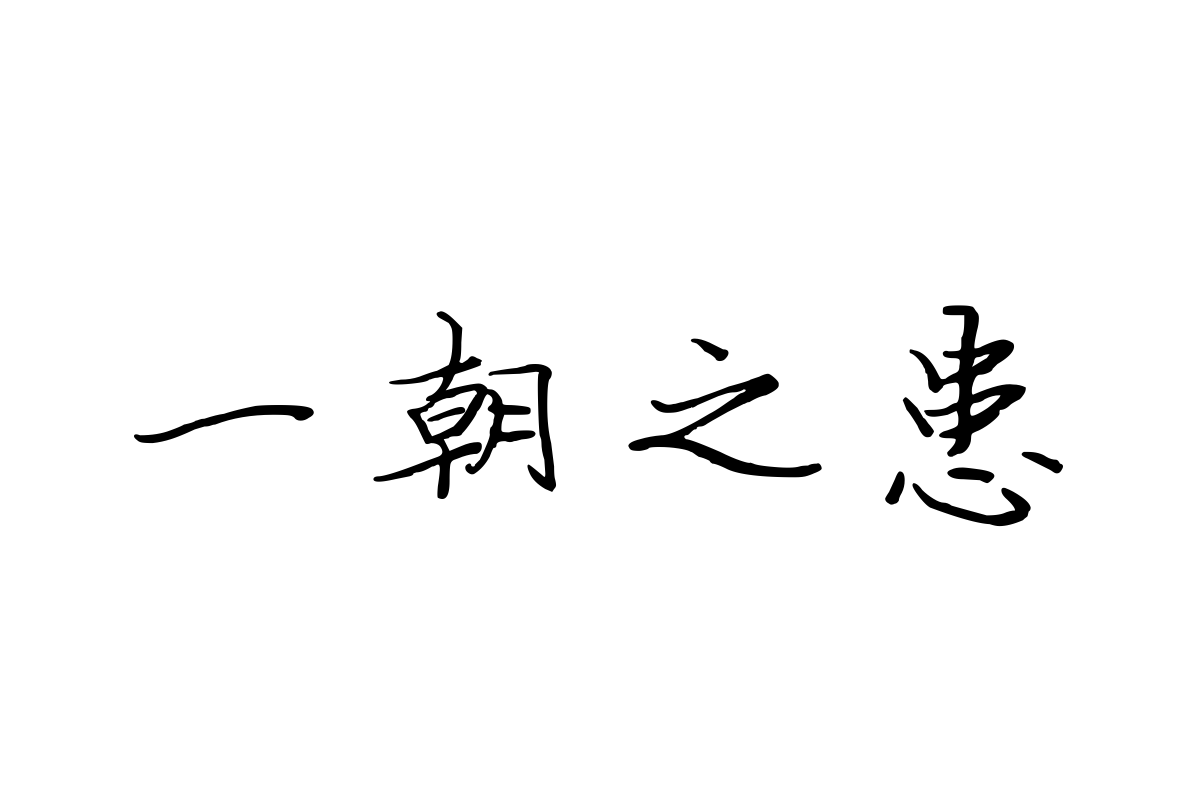
三极麒麟楷书字体是一种具有独特风格的中文书法字体,它融合了传统楷书的规范性和现代设计元素。这种字体的特点是笔画流畅、结构严谨,给人一种优雅而庄重的感觉。
三极麒麟楷书字体的特点包括:
1. 笔画流畅:该字体的笔画线条流畅自然,没有过多的装饰和修饰,给人一种简洁而清晰的视觉效果。
2. 结构严谨:该字体的结构严谨,每个字的笔画都按照一定的规则进行排列,使得整个字体看起来整齐有序。
3. 风格独特:三极麒麟楷书字体结合了传统楷书的规范性和现代设计元素,形成了一种独特的设计风格。
4. 易于识别:由于其独特的风格,三极麒麟楷书字体在视觉上具有较高的辨识度,容易让人一眼就能看出其特点。
5. 适用范围广泛:三极麒麟楷书字体适用于各种场合,如书籍、杂志、广告等,具有较强的实用性。